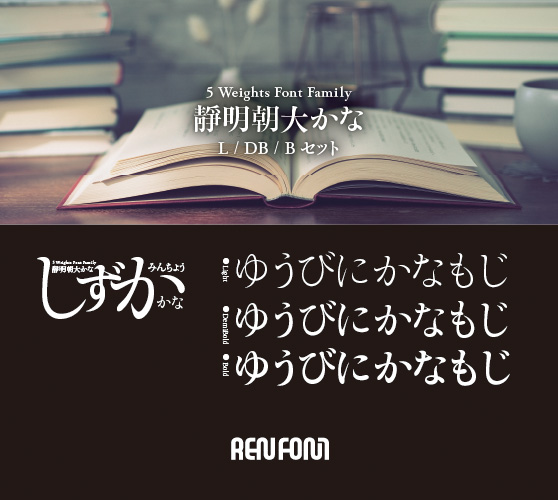
明朝体
靜明朝大かな-中・小見出し用3ウェイトセット(L/DB/B)
「小説などの長文を組んでもらいたい」とのコンセプトをもとに開発しました。靜明朝には「大かな」と「小かな」があり、このフォントは横組みに適した「大かな」です。横組みの長文に使ってみてください。落ち着いた、それでいながら訴求力のある紙面になるはずです。縦組み、横組みともプロポーショナル加工を加えました。また、ペアカーニングも緻密にほどこしてあります。中・小見出し用3ウェイトセット。